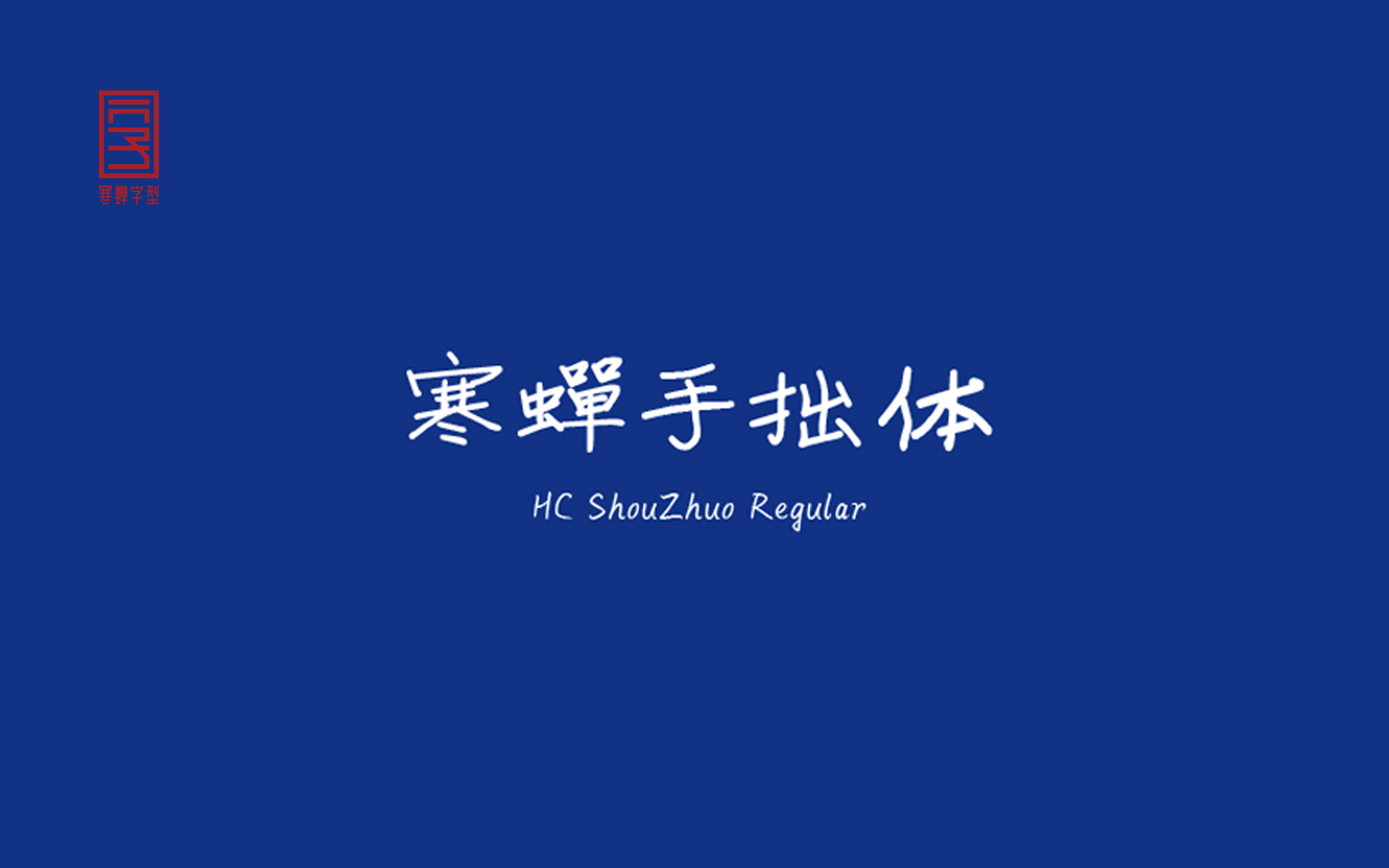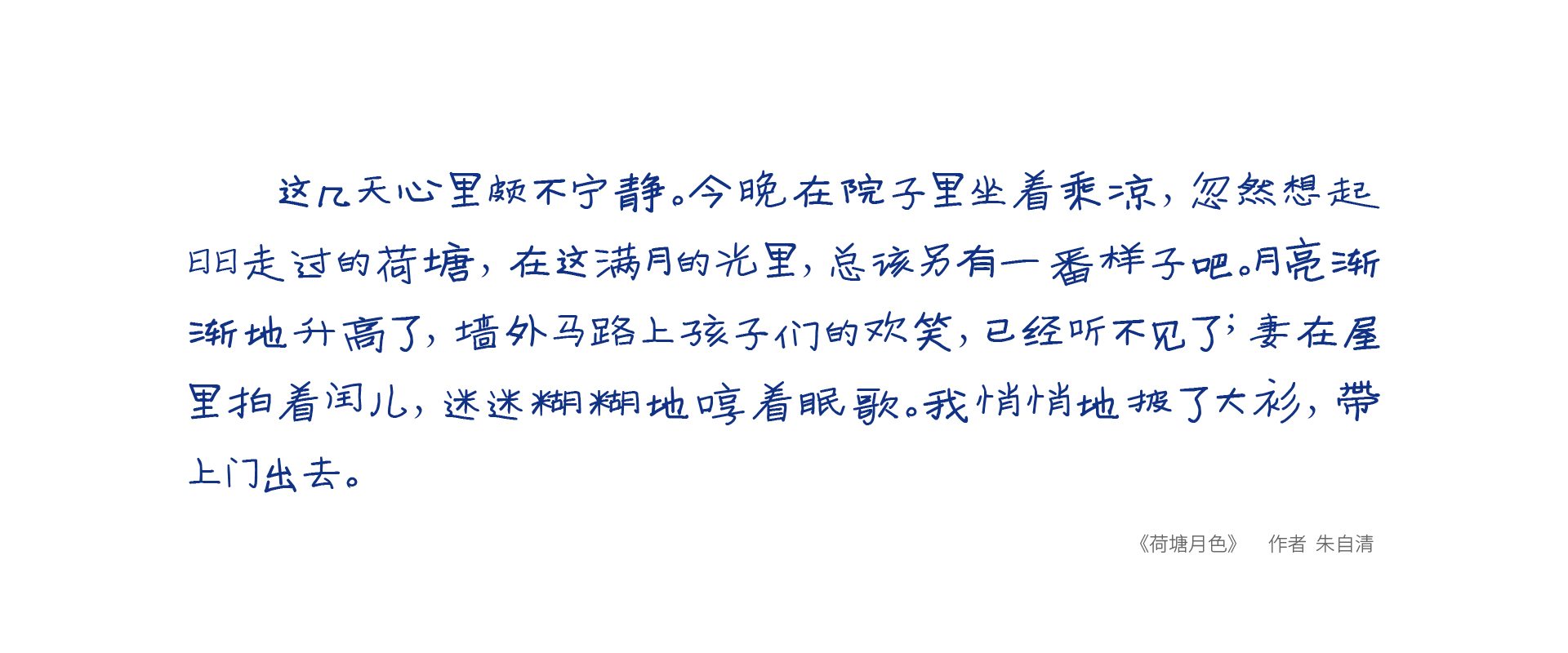
寒蝉手拙体(ChillZhuo)是一款手写风格的中文免费商用字体,该字体以创造的笔意和结构完成,风格独特,给人一种逼真手写的视觉体验,作者是来自深圳的设计师萧熠Siue。
寒蝉手拙体(ChillZhuo)基于中华人民共和国GB2312-80字符集标准,共收容字形7586个。
寒蝉手拙体(ChillZhuo)字形展示